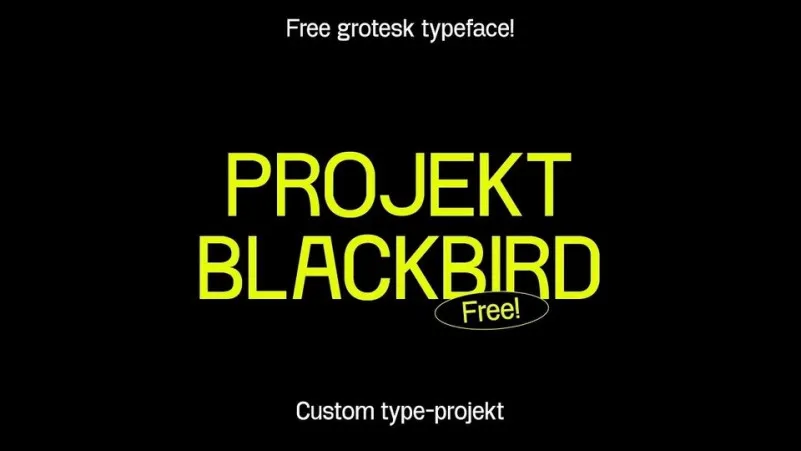
A Project Blackbird é uma fonte de sans-serif projetada por Leonit Gashi que se destaca pela sua versatilidade e facilidade em trabalhar tanto nos tamanhos menores quanto maiores. Esta elegante escolha de tipo, com características humanistas, foi criada para atender a diversos propósitos visuais. A fonte é perfeita para aplicações que incluem branding de marcas, projetos de logotipos, estamparia de produtos e cabeçalhos de revistas. Também pode ser usada com simplicidade em overlay textual sobre imagens de fundo, tornando o texto ainda mais atraente e agradável ao olhar. Seja você um designer criativo buscando dar um novo twist à sua identidade visual ou um especialista em logotipos procurando uma fonte moderna, essa é a escolha perfeita. Project Blackbird está aqui para fornecer estilo, simplicidade e facilidade de uso sem sacrificar o design ou a qualidade.